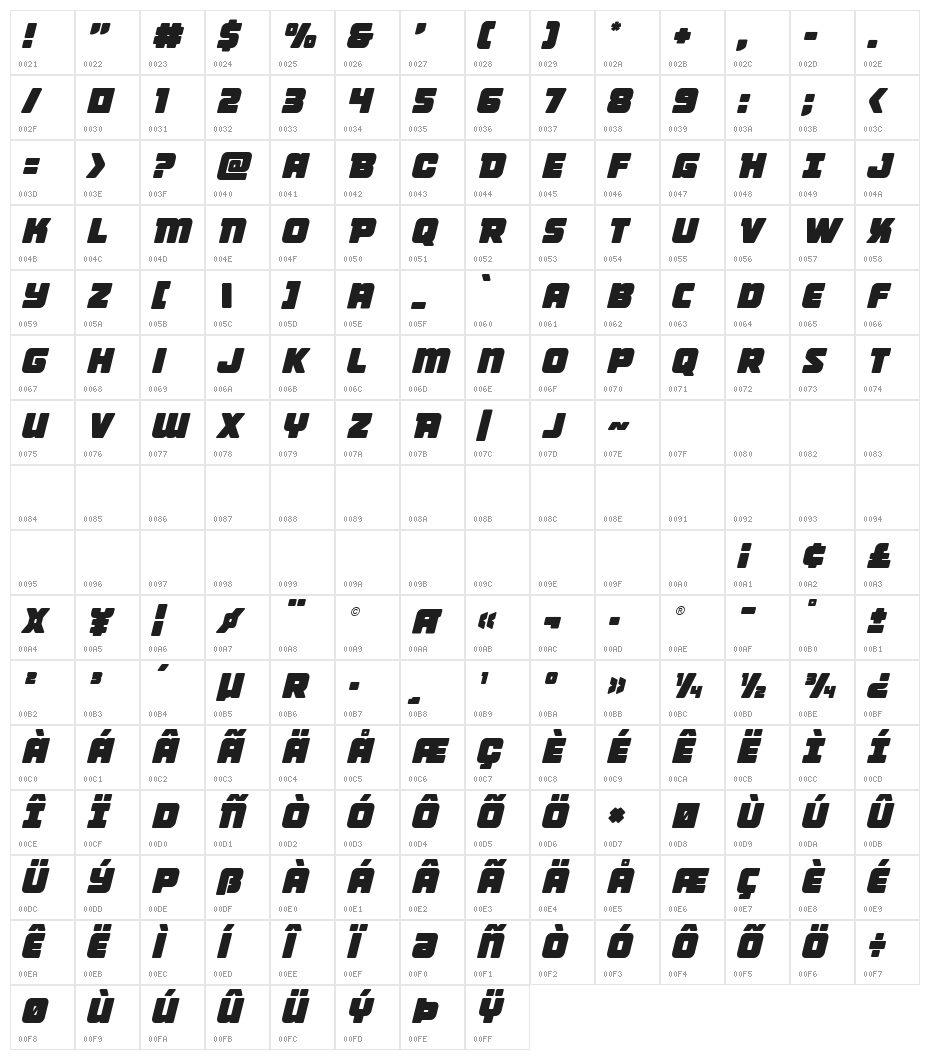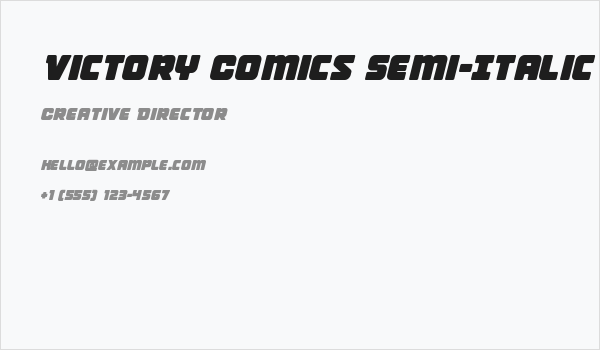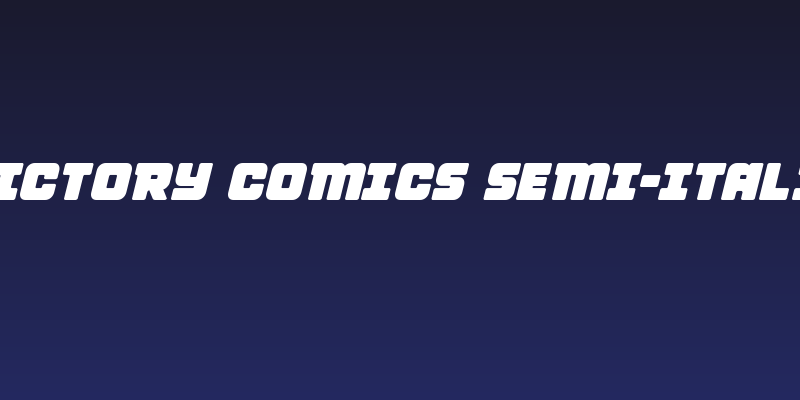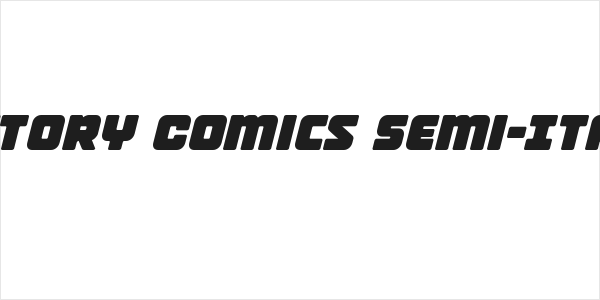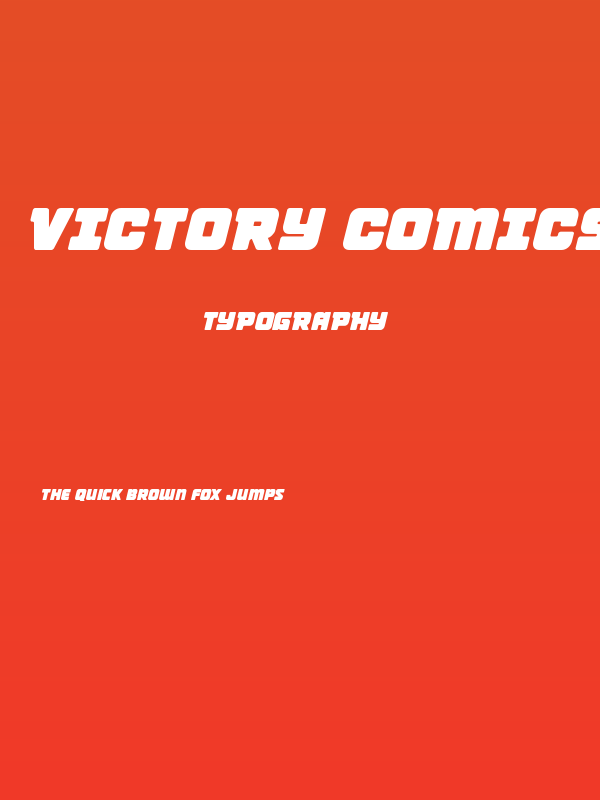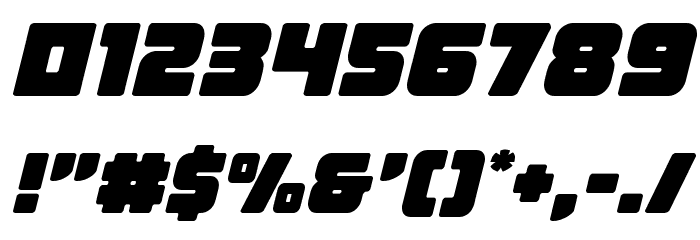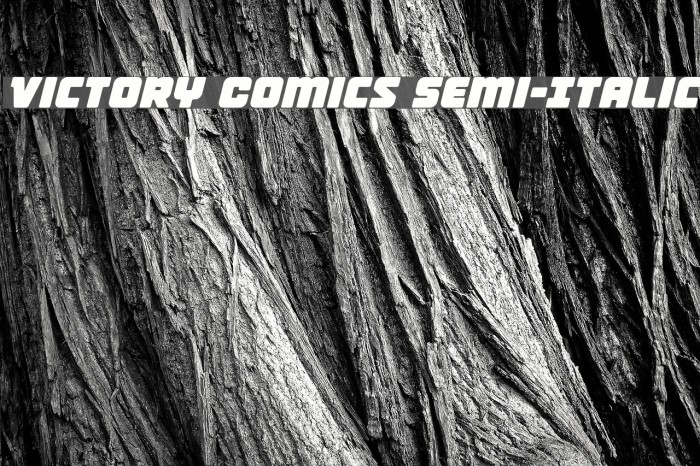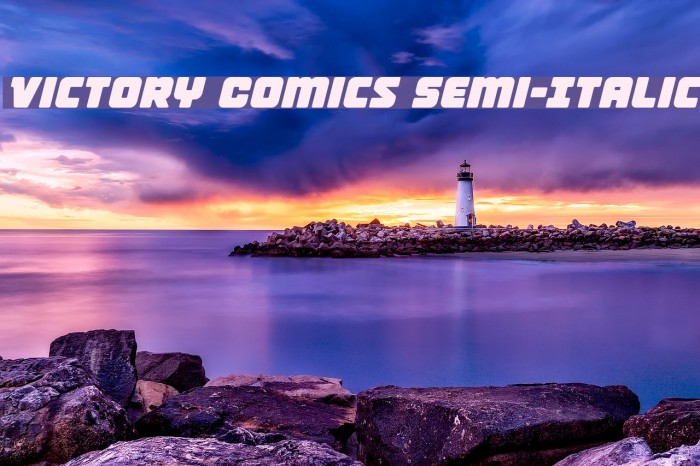
Victory Comics Semi-Italic Font
Iconian Fonts - Daniel Zadorozny - www.iconian.com
| Proyectos propuestos | Perfect for comic books, posters, video game titles, and branding that requires a bold and energetic look. |